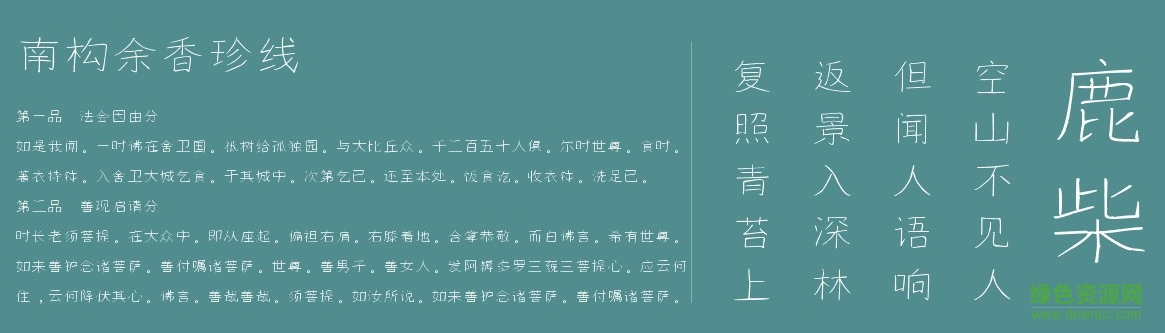
南構(gòu)余香珍線體是一款南構(gòu)出品的手寫(xiě)字體,散漫又帶有拘謹(jǐn),看單個(gè)字體感覺(jué)不夠嚴(yán)謹(jǐn),但是當(dāng)大家看整篇行文時(shí),又自帶氣息,平衡而優(yōu)雅。歡迎大家來(lái)綠色資源網(wǎng)下載使用!
南構(gòu)余香珍線是一款線體手寫(xiě)體字體,中規(guī)中矩中帶著一種爛漫的手寫(xiě)風(fēng),剛毅而嚴(yán)謹(jǐn)?shù)囊唤z不茍。